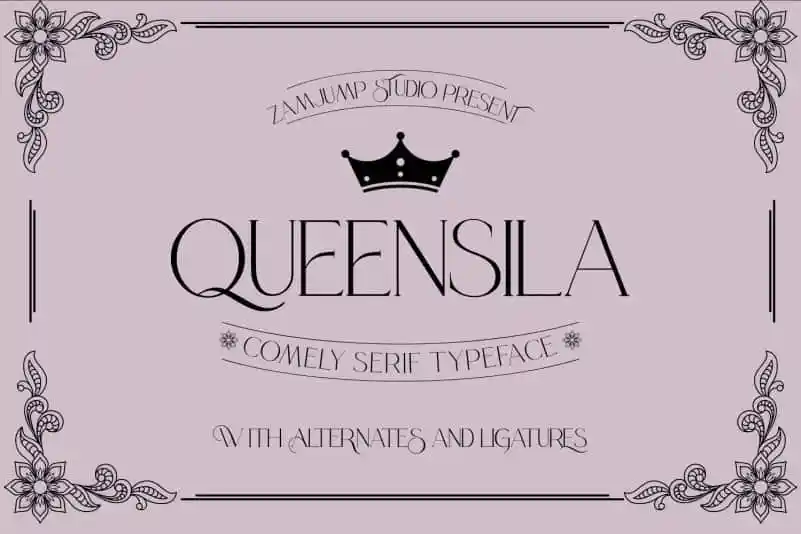
A Queensila Serif Font é uma escolha moderna para quem busca elegância em suas marcas e identidades corporativas. Criação do designer zamjump, esta fonte serif incorpora ligações de caracteres e alternativas que dão um toque de estabilidade à sua marca. Essa é uma fonte versátil projetada para diversos contextos, desde grandes tamanhos até pequenos detalhes, garantindo sempre um visual elegante e sofisticado. Ideal para branding, logos e materiais gráficos onde a elegância clássica se destaca. Escolha Queensila Serif para dar ao seu design o tom certo de confiabilidade e profissionalismo.